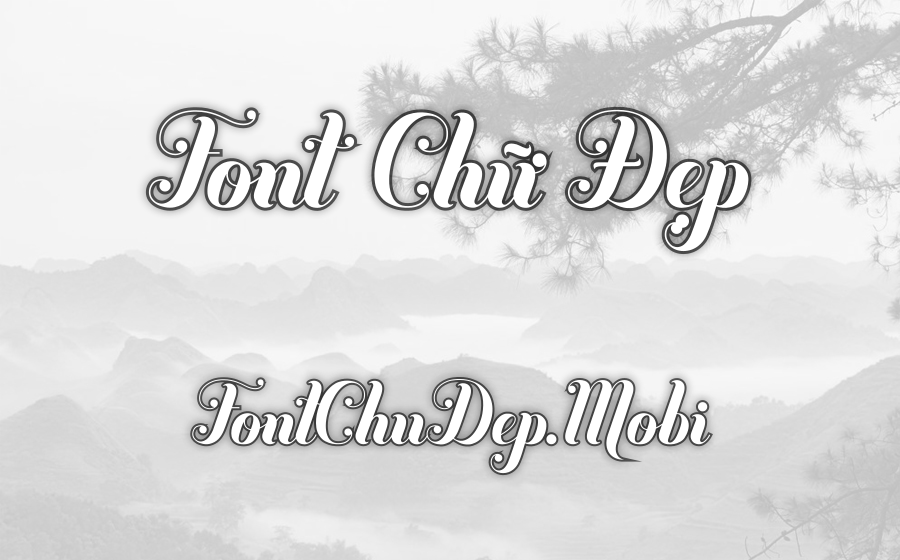
Font HLT Buttermilk Việt Hóa
HLT ButterMilk
Phông chữ Buttermilk, một tác phẩm đầy mê hoặc và tinh tế của Jessica Hische từ năm 2008, chắc chắn sẽ làm say lòng bất kỳ ai yêu thích sự mềm mại và thanh lịch. Được thiết kế với đường nét uyển chuyển, Buttermilk tạo ra cảm giác dịu dàng và sang trọng, hoàn hảo cho nhiều thể loại dự án thiết kế. Điều đặc biệt là với sự Việt hóa từ HLT, phông chữ này giờ đây đã hỗ trợ đầy đủ các ký tự tiếng Việt, mở rộng cơ hội sáng tạo cho các nhà thiết kế khi làm việc với ngôn ngữ đa dạng.
Tôi đã có cơ hội trải nghiệm phông chữ Buttermilk qua chia sẻ từ cộng đồng FontChuDep.mobi. Phông chữ này thực sự là một nguồn cảm hứng thiết kế vô tận. Các ký tự với nét cong mượt mà và tinh tế của Buttermilk đem đến sự thân thiện và gần gũi, rất lý tưởng cho những dự án như thiệp mời, bìa sách, poster, logo và các sản phẩm quảng cáo đầy cuốn hút. Không chỉ vậy, với khí chất vui tươi và lãng mạn, Buttermilk còn rất thích hợp cho các dịp lễ hội, lễ tình nhân, sinh nhật hay Trung Thu.
Trải nghiệm thực tế từ phông chữ Buttermilk còn cho thấy sự tác động mạnh mẽ của nó trong lĩnh vực quảng cáo, thiết kế thiệp cưới, giáo dục, và công nghệ. Mỗi thiết kế sử dụng Buttermilk đều khoác lên mình một diện mạo chuyên nghiệp và ấn tượng, góp phần nâng tầm cho sản phẩm và thương hiệu. Với những cảm nhận sâu sắc và đa chiều, tôi thực sự tin rằng Buttermilk là một lựa chọn không thể bỏ qua cho mọi nhà thiết kế tìm kiếm sự khác biệt và tinh tế.